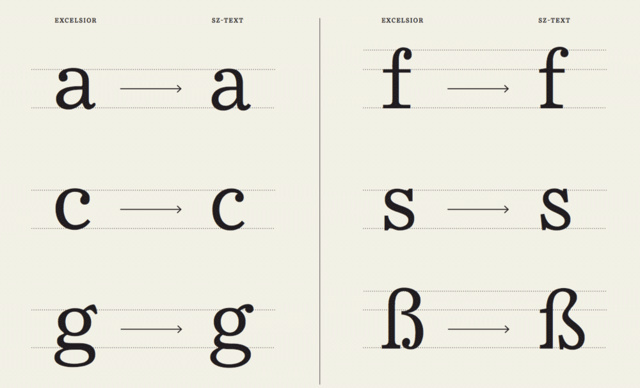
Neues Layout der Printausgabe: Ab Montag erscheint die SZ in dezent anderem Gewand
zugegeben, da s hat charakter aber der ist bei den anderen buchstabenformen nicht konsequent durchgezogen.
ich weiss nicht was an dem alten s verkehrt war, das s hätte man nicht extra ändern müssen. jetzt sieht es aus wie ein fremdkörper, irgendwie humanistische form aber dieser wurde bei den restlichen buchstaben nicht konsequent durchgezogen. wie kathrin schon schrieb, es wirkt 'zögerlich'.
Doch, es gibt neben einem einstöckigen g noch zwei Versionen der komplexen Form. In Deinem Beispiel sieht man nur die Andere »für die Lauftexte«. (Siehe Fontblog-Kommentar von Henning Skibbe, einem der beiden verantwortlichen Schriftgestaltern.)
vielleicht verstehe ich diesen kommentar falsch, aber der sagt meines erachtens: es gibt ein ›g‹ mit schlichtem strich für die fließtexte (= sz text). die headline-antiqua (= sz serif) hat ein anderes ›g‹ mit tropfenförmigem ohr. das heißt: die abbildung, die sich explizit auf die sz text bezieht und ein ›g‹ mit tropfen zeigt, deckt sich nicht mit der verwendung in der zeitung.
Ich finde das ›s‹ guckt sogar fast grummelig ...
Stimmt, so könnte man das auch sehen. :-?
Ich sehe es genau anders herum. Hätte man das ‚s‘ so gelassen, wäre es ein Fremdkörper. Schließlich ist das a, c, e, … auch nicht mehr so „ausgespannt“. Aber jetzt, wo ihr das sagt, sehe ich auch, dass es noch ein klein wenig unbeholfen zurückschreckt. :-)
Der Gesprächsbedarf für ein Interview steigt.
Ist so etwas bei den Produktionsbedingungen einer Tageszeitung nicht Blödsinn?
Ich bin trotzdem vorsichtig, ein falsches ‚g‘ in der Abbildung zu unterstellen. Wie gesagt, das müsste man einfach noch mal erfragen.
was soll man da erfragen? ich schaue in die zeitung, sehe ein anderes ›g‹ als in der abbildung und gehe davon aus, dass es (versehentlich) eine nicht finale fassung des buchstaben in die abbildung, nicht aber ins blatt geschafft hat. wenn sie ihren lesern zeigen wollten, wie die schriftart, die sie ab sofort jeden tag im fließtext sehen werden, im detail aussieht, ist das jedenfalls nicht ganz geglückt.
seh ich eigentlich auch so, die SZ ist ja kein werbblättchen oder wird in einer hinterhofdruckerei gedruckt aber die werden sich schon was dabei gedacht haben.
Ich versteh die Frage nicht ganz … was befürchtest du, dass passieren könnte?
Ich vermute, Dieter fragt sich, ob solche Feinheiten beim Druck auf Zeitungspapier überhaupt rauskommen. Aber das haben die am Redesign Beteiligten sicherlich mit Andrucken auf Originalpapier getestet. Schätze ich. Aber das können wir ja zum Glück im Interview alles fragen. :-)
Das wär’ möglich … vielleicht meint er auch, dass es in der Hektik gar nicht möglich ist, die verschiedenen Formen jeweils korrekt einzusetzen. Aber er wird mich sicher aufklären ;-)
Sowas regelt man doch mit Formatvorlagen, in denen man einstellt, welche Variante verwendet werden soll. Würde ich zumindest machen.
Genau das habe ich mich gefragt.
Die Frage ist auch berechtigt. Glücklicherweise kann das über Formatvorlage, GREP, etc. automatisiert werden.
Genau davon bin ich auch die ganze Zeit ausgegangen. Und offensichtlich wird es auch so gemacht:
Das ‚g‘ mit dem Haken/Tropfen …
… ist über Opentype anzusteuern, wird aber nur in den Headlines eingesetzt.